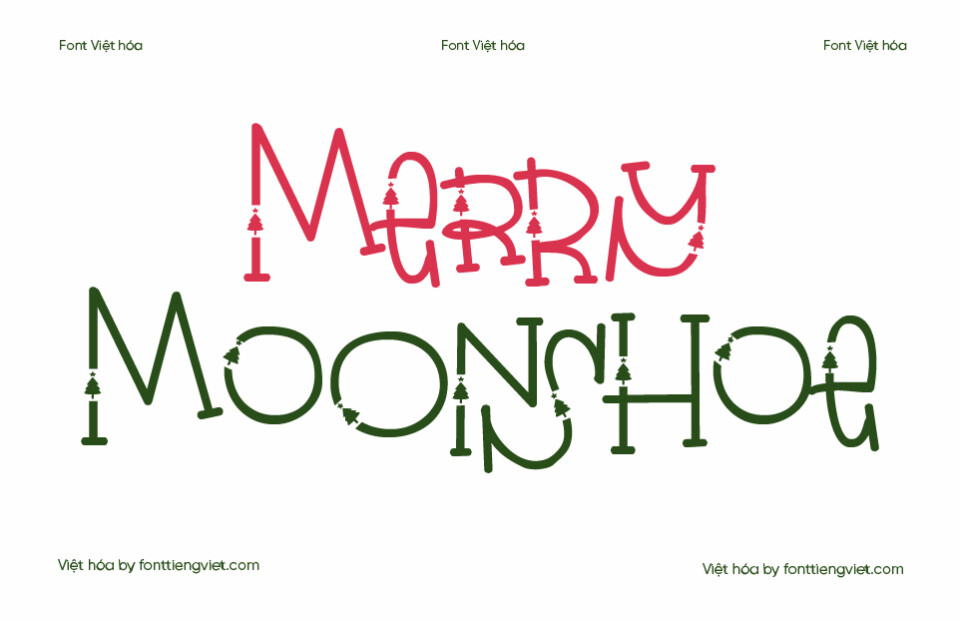
Font Việt hóa 1FTV ZP Merry Moonshoe
Giới thiệu về bộ Font Việt hóa 1FTV ZP Merry Moonshoe
Trong thế giới thiết kế đồ họa, việc lựa chọn một bộ Font Miễn Phí chất lượng luôn là ưu tiên hàng đầu của các bạn trẻ và thầy cô giáo. Font Việt hóa 1FTV ZP Merry Moonshoe nổi lên như một hiện tượng nhờ phong cách viết tay đầy ngẫu hứng và mềm mại. Đây là bộ phông chữ mang đậm dấu ấn cá nhân, giúp các tác phẩm trở nên gần gũi và giàu cảm xúc hơn bao giờ hết. Với sự chỉn chu trong từng nét vẽ, bộ chữ này hứa hẹn sẽ làm hài lòng những người yêu cái đẹp.
Đặc điểm nổi bật của Font Việt hóa 1FTV ZP Merry Moonshoe
Bộ Font Việt hóa 1FTV ZP Merry Moonshoe sở hữu các đường nét uyển chuyển, mô phỏng lại nét bút mực trên giấy một cách chân thực nhất. Khoảng cách giữa các ký tự được căn chỉnh hợp lý, giúp văn bản dù ở định dạng tiêu đề hay đoạn văn ngắn đều giữ được sự thông thoáng, dễ đọc. Đặc biệt, quá trình Việt hóa đã được tối ưu hoàn toàn, không còn lỗi dấu hay các khoảng hở khó chịu, giúp các bạn học sinh dễ dàng áp dụng vào bài thuyết trình hoặc làm thiệp tặng thầy cô.
Ứng dụng đa dạng trong học tập và thiết kế
Sáng tạo nội dung giáo dục sinh động
Việc sử dụng Font Việt hóa 1FTV ZP Merry Moonshoe trong các tài liệu giảng dạy giúp bài học trở nên sinh động và bớt khô khan hơn. Thầy cô có thể dùng bộ chữ này để trang trí bảng tin, làm tiêu đề cho các slide bài giảng PowerPoint hoặc thiết kế các chứng nhận khen thưởng cho học sinh. Sự mềm mại của bộ chữ giúp kích thích thị giác và tạo sự hứng thú cho người xem ngay từ cái nhìn đầu tiên.
Thiết kế cá nhân và thiệp chúc mừng
Nếu bạn đang tìm kiếm một phông chữ để làm Bullet Journal hay thiết kế thiệp chúc mừng, Font Việt hóa 1FTV ZP Merry Moonshoe là lựa chọn không thể bỏ qua. Nét chữ tựa như lời nhắn gửi yêu thương, rất phù hợp cho các dịp lễ Tết, trung thu hay kỷ niệm trường lớp. Bạn có thể phối hợp bộ chữ này với các tông màu pastel để tạo nên vẻ ngoài thanh lịch và hiện đại cho sản phẩm của mình.